השאלון עם יונתן לייבה
הכירו את יונתן לייבה, בן 23, נולד בחיפה וכשהיה בן חמש עבר לגור במשגב, עד היום. יונתן לומד בשנה ב׳ לתקשורת חזותית בויצו, שלמעשה הפכה לא מזמן לחלק מאוניברסיטת חיפה. הוא מתעסק בעיקר בפרינט, פוסטרים וקצת מושן, אבל תמיד נהנה לחקור פורמטים ומדיומים חדשים. מה שיונתן הכי אוהב בעיצוב זה את הדינאמיות שבמקצוע – את החופש לנסות, לטעות, ולגלות דברים חדשים גם אם לא תמיד הכול עובד. כשיונתן לא מעצב או עובד, הוא אוהב להכין פיצה, ללכת לים ולישון.
על איזה פרויקט מעניין עבדת לאחרונה?
לאחרונה עיצבתי פוסטר לאחד הקורסים, שבו התבקשנו להמחיש איך אהבה נראית באמצעות ASCII ART. אני ממש מרוצה מהתוצאה – בדרך כלל אני די קשוח עם עצמי, אבל הפעם זה דווקא נתן לי פרספקטיבה על מה שאני כן מסוגל לעשות. וחוץ מזה, הדפסתי את הפוסטר בריזו – שזה תמיד פלוס. 🙂
אני תמיד מתמלא בהשראה כשאני רואה פרויקטים שאני ממש אוהב. כל פעם שאני רואה פגמ"ר שהוא סרט בתלת־ממד, אני אומר לעצמי מחדש שאני אלמד בלנדר, וכל פעם מחדש לא קורה עם זה כלום.
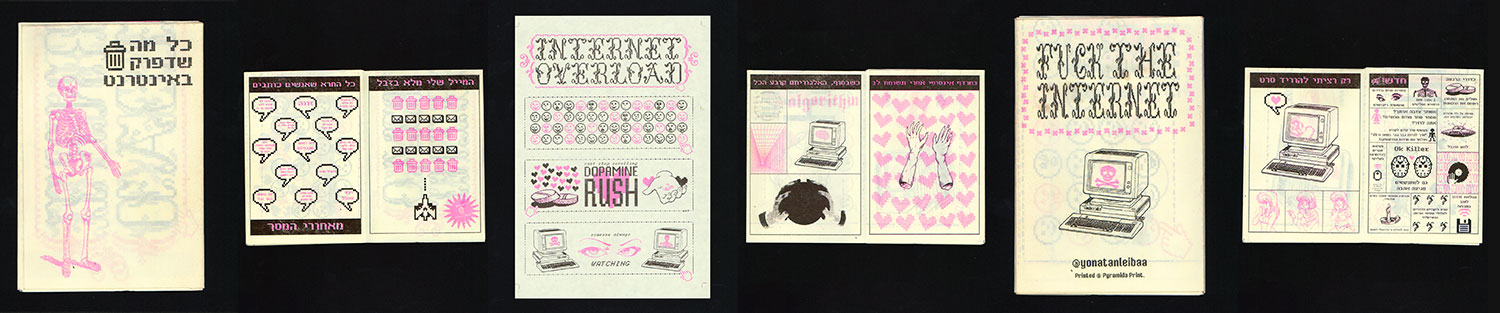
פרויקט שלי משנה א' – הפנזין "כל מה שדפוק באינטרנט". בקורס "יסודות התפישה החזותית" קיבלנו בריף: לעשות מחאה על נושא כלשהו. אני בחרתי לעשות את המחאה שלי על האינטרנט, בתור אחד שסוג של גדל לתוך האינטרנט. עיקר הפנזין עוסק ב... כל מה שדפוק באינטרנט. כל עמוד עוסק בבעיה אחרת שכולנו נתקלים בה בשימוש יום יומי באינטרנט. כל השפה הגרפית בפנזין מפוקסלת ובאסתטיקה דיגיטלית ישנה, והפנזין עצמו מודפס בריזו, דבר שממש תורם לתחושה הדיגיטלית והמשובשת. בכללי, אני חושב שיש משהו קסום בלקחת דבר שאנחנו רגילים לראות במסכים בדרך כלל, כמו פיקסלים, ולהביא אותו לעולם האמיתי כדבר דפוס. פיקסלים יכולים לעבוד ככלי נהדר להפשטה ולהעברת דימויים בצורה מקורית ויצירתית שגם נראית טוב, ואני תמיד אוהב לראות שימוש בהם, במיוחד בפרינט.
מה משך אותך לתחום?
תמיד הייתי ילד יצירתי. אהבתי לצייר, לכתוב, והסביבה שלי גם מאוד התלהבה מהדמיון שלי. בכיתה י׳, כשצריך היה לבחור מגמה, בחרתי במגמת העיצוב בתיכון – ומאז, פחות או יותר, הכול היסטוריה.
באיזה פונט אתה רוצה שיכתבו על המצבה שלך?
פונט קונצ׳רטו של עדי עובדיה.
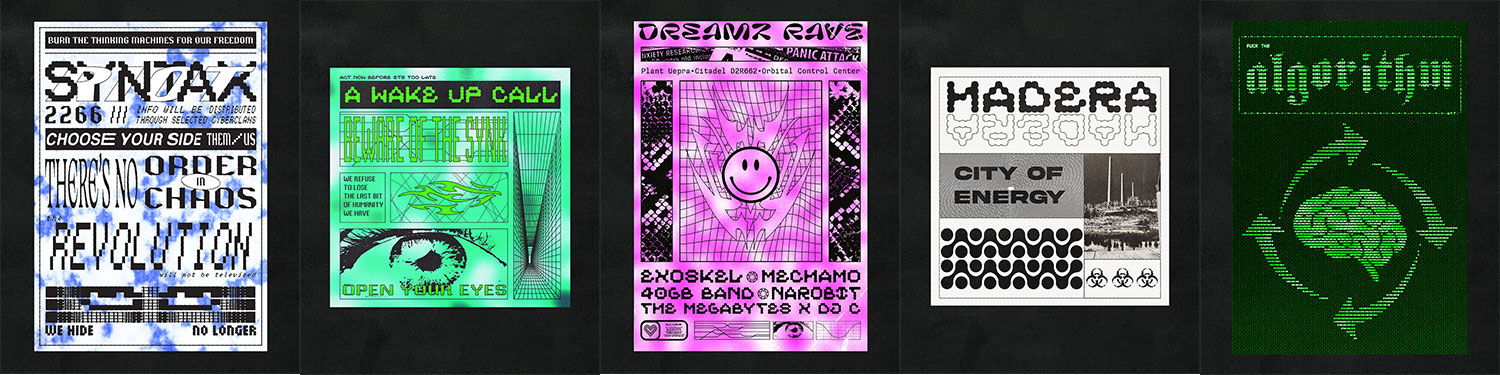
בדרך כלל כשאני יושב לעבוד על פוסטר, אני ישר ניגש לדימויים, טיפוגרפיה וקומפוזיציה. הקונספט נבנה תוך כדי. כן יש לי תמונה מסוימת בראש של איך אני רוצה שהתוצר הסופי ייראה, אבל אני בעיקר מתמסר לתהליך ונותן להכול להיבנות שלב אחרי שלב. את ההשראה לפוסטרים אני לוקח מפליירים ופוסטרים של מסיבות טכנו ורייבים ישנים. אני מאוד מתחבר לאסתטיקה המחוספסת והמחתרתית יותר. מקסימליזם במלוא העוצמה – להכניס כמה שיותר דימויים, לעבוד עם טקסטורות, צבעים משוגעים ולהפציץ בטיפוגרפיה. אני חושב שלעצב דווקא ממקום של הקצנה או חוצפה יוצר דברים הרבה יותר מעניינים מאשר עבודה שהיא מדויקת לגמרי. זה עיקרון שאני מאוד מתחבר אליו באסתטיקה הברוטליסטית והמקסימליסטית שמאפיינת את התקופה הזו. בכללי, אני מאמין שיש משהו מאוד משחרר בליצור מתוך תחושה ולא לפי חוקים, במיוחד כשאנחנו רגילים לעבוד לפי כללים ומערכות שנקבעו מראש.
יש לך המלצה מוזיקלית?
Magdalena Bay – אני שומע אותם כבר כמה שנים, ומעבר למוזיקה המעולה שלהם, יש להם אסתטיקה מאוד ספציפית שאני מת עליה.
איך עולם העיצוב ייראה בעוד עשור?
העולם יהיה מעניין יותר, עם כישרונות וטרנדים חדשים. מאמין שגם מושן ועיצוב אינטראקטיבי יתפסו מקום הרבה יותר משמעותי. אני לא מאמין בכל נבואות הזעם על זה שהבינה המלאכותית תחליף את המעצבים – בסופו של דבר, זה עוד כלי שנלמד להשתמש בו.